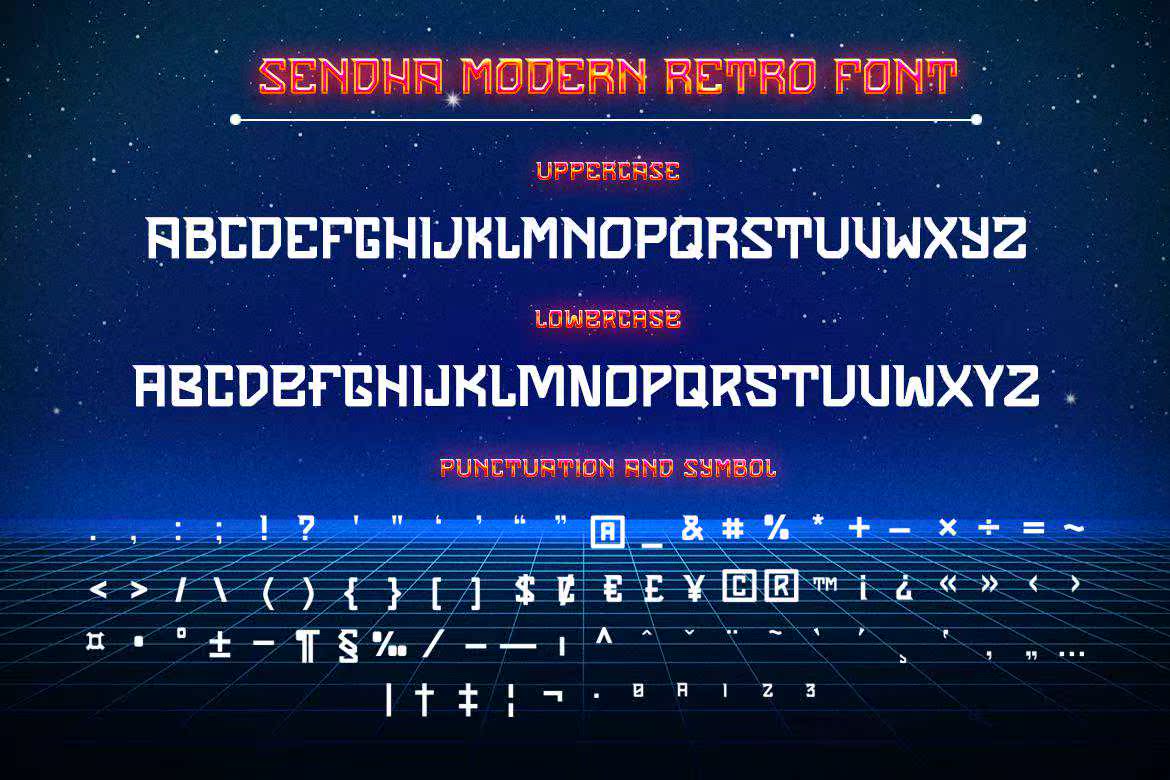
发送给HaiSafe的内容可能与Ye不一样,并且可能已经习惯了字体的提示和Blazing设计。内容功能是一种3D设计,它可以完美地显示用户的注意,并最终将死亡增加到新的可能性。是否用于运动,创作音乐,甚至是创作杂志封面。向Hai发送完美的选择,以满足观众的需求,并创作出愉悦感和明亮感。向Hai发送可能与Ye不一样的内容,并且可能习惯于字体的提示和Blazing设计。这些内容功能是一种3D设计,能够完美地显示用户的注意力,最终,无论是用于体育、音乐创作还是杂志创作,都会让你的梦想成为新的可能。这是一个完美的选择,可以让你更好地适应观众,让你感受到快乐和光明。